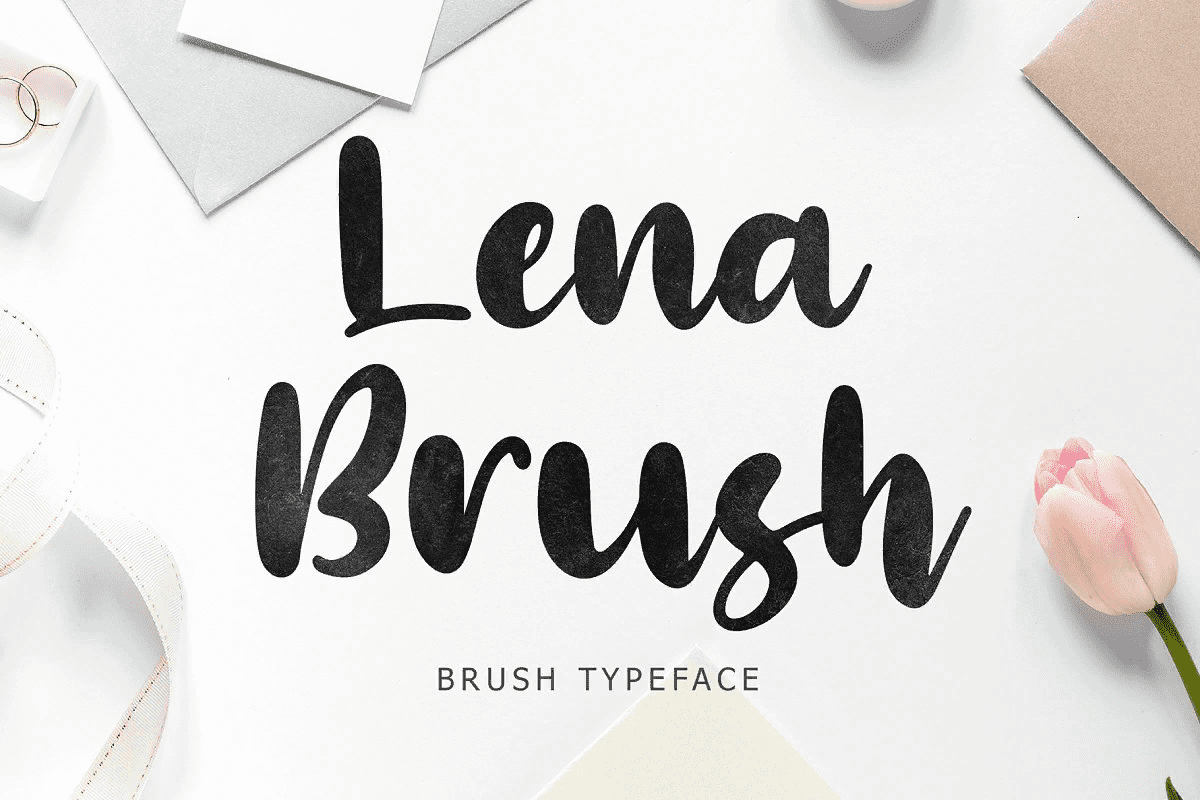
Название: Lena Brush Font (2021)
Lena Brush - это шрифт в виде кисти, который сделает ваш текст элегантным, роскошным и современным.
Lena Brush идеально подходит для брендинговых проектов, логотипов, свадебных дизайнов, постов в социальных сетях, рекламы, упаковки товаров, дизайна футболок, дизайна продуктов, этикеток, фотографий, водяных знаков, приглашений, канцелярских товаров и любых других проектов.
Название: Lena Brush Font (2021)
Lena Brush - это шрифт в виде кисти, который сделает ваш текст элегантным, роскошным и современным.
Lena Brush идеально подходит для брендинговых проектов, логотипов, свадебных дизайнов, постов в социальных сетях, рекламы, упаковки товаров, дизайна футболок, дизайна продуктов, этикеток, фотографий, водяных знаков, приглашений, канцелярских товаров и любых других проектов.